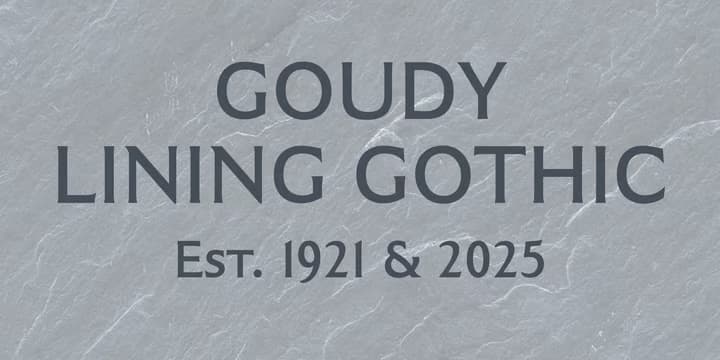
Goudy Lining Gothic
クラシカルで品の良いサンセリフ(?)。碑文風味のあるクラシカルな骨格のグリフで、ほぼほぼモノラインのストロークにほんの僅かなセリフ…のようなものが付いている。フレアセリフと言った方が良いかも。アメリカの巨匠、Frederic Goudy が1921年に発表した書体をデジタル化したものだそうだ。デジタル化にあたりスモールキャップスを追加し、1つしかなかったウェイトも増やした。スモールキャップスのxハイトが結構小さめでこれまた品が良いので、大文字だけよりはそっちも含めて組んだ方がいいかもしんない。7ウェイト。